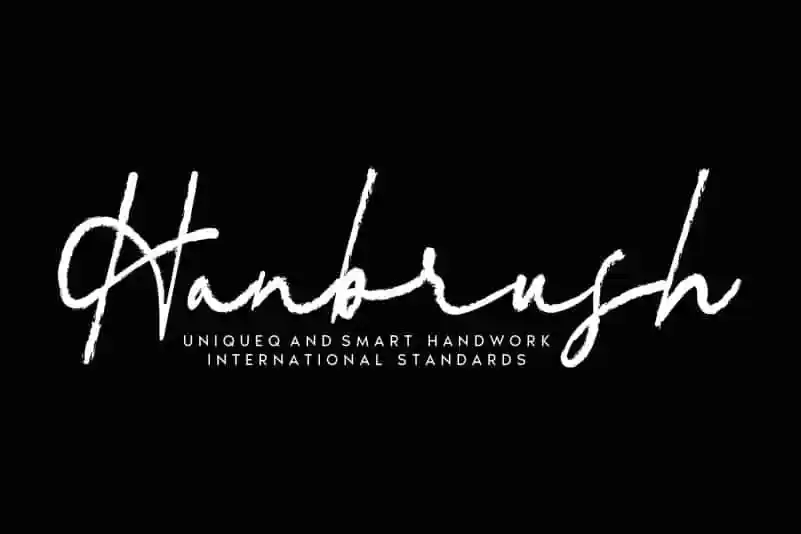
Hanbrush Script Font – Fonte Grátis
Hanbrush Script Font
Descubra Hanbrush Script Font, uma fonte brush criada especialmente para você. Esta exquisiteira é a criação única de andikastudio, oferecendo uma experiência singular na hora de escrever e desenhar com texto. Seja em um projeto editorial, ilustração ou até mesmo no design gráfico, Hanbrush Script Font irá adicionar um toque especial à sua obra. Com traços arredondados e linhas fluidas que se movem suavemente, esta fonte é perfeita para quem busca algo mais além da tipografia tradicional. Teste suas habilidades de criatividade com Hanbrush Script Font – uma escolha inteligente que certamente não deixará sua obra em falta.